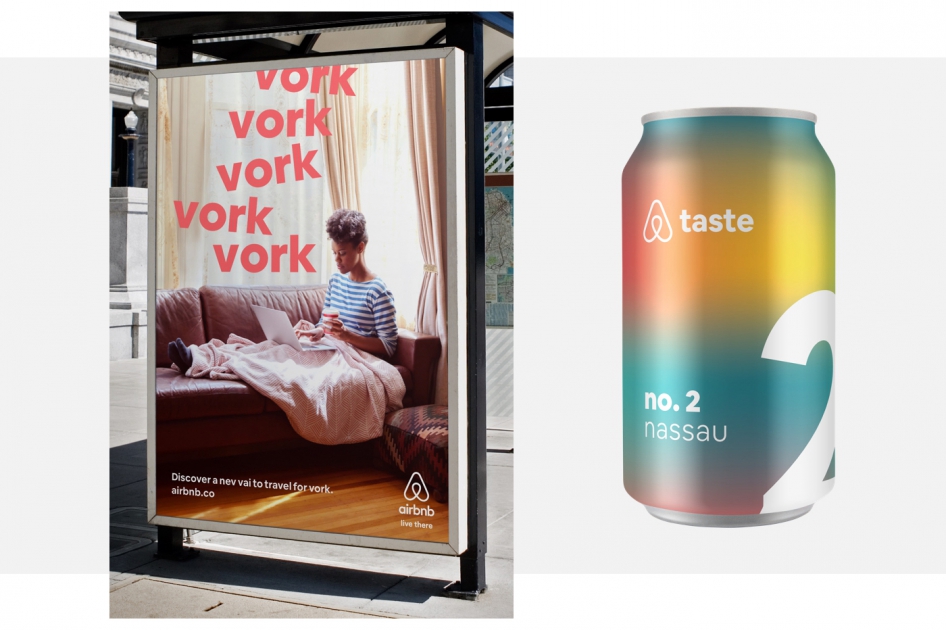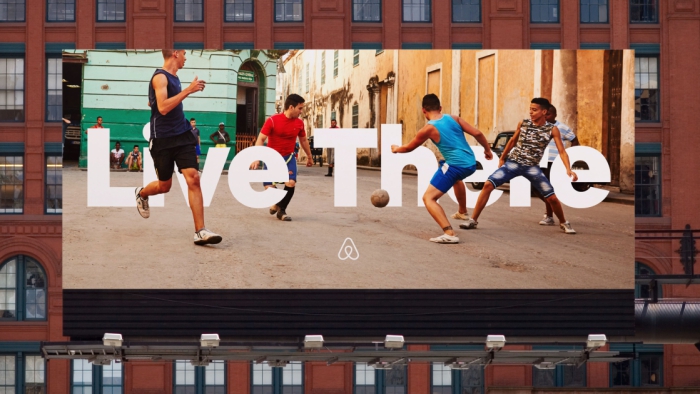
Сервис аренды жилья Airbnb в партнёрстве с дизайн-студией Dalton Maag разработал свой собственный шрифт Cereal. Компания будет использовать его во всех рекламных брендированных материалах.
В Airbnb объяснили, что собственный шрифт понадобился компании для бизнес-целей: шрифт сервиса должен быть узнаваемым и разборчивым на всех платформах, то есть одинаково хорошо выглядеть в онлайн и офлайн материалах. По словам дизайнеров, продукт получил «мощную обработку, которая подчеркивает ценности бренда».
«Наша работа чрезвычайно типографична. Люди сталкиваются с брендом на различных носителях, начиная с ресурсов в интернете, заканчивая рекламой в метро. Перед нами стояли конкретные бизнес-задачи — сделать бренд отличаемым, удобочитаемым и узнаваемым. Для этого не подходили никакие доступные шрифты. Мы хотели такой шрифт, который будет отражать индивидуальность бренда, поэтому мы решили создать свой собственный», — рассказали в компании.
Пока новый шрифт работает только с латиницей, но в дальнейшем он будет поддерживать и другие языки, в том числе арабский, китайский и кириллицу.
Николас Зеусс, дизайн-директор московского офиса Landor:
«Мы видим, что всё больше и больше компаний идут подобным путем и создают собственный шрифт как часть визуальной идентичности бренда.
Шрифт является важной частью дизайн-системы бренда, такой же важной как, например, логотип или цветовая палитра. Шрифты способны сами по себе быть носителями определенных ценностей и смыслов. Однако многие бренды используют невыразительные шрифты с бесплатной лицензией и, тем самым, теряют свой характер, становятся похожими на других.
Новый шрифт Airbnb Cereal отлично отображает современный и человечный характер бренда и в целом вызывает положительные эмоции. Airbnb сможет использовать этот шрифт на разных платформах и для разных целей, что одновременно придаёт бренду гибкость и узнаваемость.
Многие бренды не видят финансовой выгоды от создания собственного шрифта на заказ и теряют возможности. Во-первых, компания таким образом может значительно сэкономить, избавивших от затрат на использование платных шрифтов. Например, стоимость использовании лицензии на шрифт для веб-площадок зависит от количества кликов и может обходиться компании очень дорого. Во-вторых, собственный шрифт является долгосрочной инвестицией в отношения с партнёрами вашего бизнеса: вы можете предоставлять им право на бесплатное использование вашего шрифта и это даст вам гарантию, что в любых коммуникациях ваш бренд будет узнаваем".